Infografías Efectivas: La Importancia de la Tipografía Adecuada
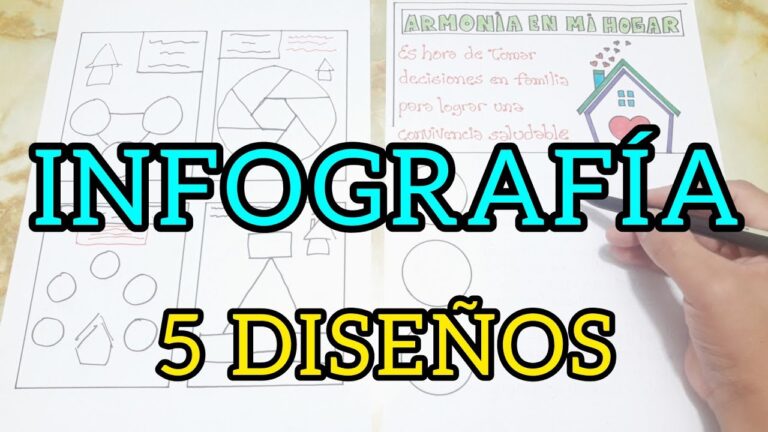
En la era de la información, el diseño de infografías con tipografía adecuada se ha convertido en una herramienta esencial para comunicar datos de manera operativa. La elección de una tipografía apropiada no solo mejora la legibilidad, sino que también refuerza el mensaje visual, capturando la atención del espectador y facilitando la comprensión de conceptos complejos. En este artículo, examinaremos cómo una tipografía bien seleccionada puede transformar una simple infografía en una poderosa narrativa visual que destaque en un mundo saturado de información.
¿Qué tipo de fuente se recomienda para una infografía?
Para una infografía operativa, es recomendable utilizar tipos de letra como Verdana, Arial o Helvética, que son sans serif y garantizan una buena legibilidad. El tamaño de la letra debería estar entre 12 y 14 puntos, lo que permite que la información sea fácilmente visible sin ser abrumadora. Además, es aconsejable reservar el uso de mayúsculas únicamente para palabras cortas y títulos, asegurando así que el contenido se mantenga claro y atractivo para el lector.
¿Qué se debe incluir en la fuente de una infografía?
En una infografía, la fuente es esencial para dar credibilidad a la información presentada, ya que señala de dónde se ha obtenido. Generalmente, se coloca en un tamaño menor y en una ubicación discreta, de manera que no distraiga la atención del lector del contenido principal. Este detalle no solo respeta los derechos de autor, sino que también permite al público profundizar en el tema si lo desea, fomentando una comprensión más rica y fundamentada de los datos expuestos.
¿Cuáles son las mejores fuentes para utilizar en infografías?
Al crear infografías operativas, la elección de la tipografía es fundamental. Las fuentes sans serif, como Roboto, Helvetica y Arial, son especialmente populares debido a su claridad y modernidad. Estas fuentes aportan un aire contemporáneo y facilitan la lectura, lo que las convierte en una excelente opción para captar la atención del espectador.
Para maximizar el impacto visual de tu infografía, es crítico utilizar estas fuentes en los lugares adecuados. Mientras que las fuentes serif suelen ser más apropiadas para el cuerpo del texto, las sans serif brillan en los encabezados de sección, subtítulos, listas y títulos. Este enfoque no solo mejora la estructura visual, sino que también guía al lector a través de la información presentada.
En resumen, la combinación de fuentes adecuadas puede transformar una infografía ordinaria en una herramienta poderosa de comunicación. Al optar por fuentes como Roboto, Helvetica o Arial para los elementos destacados, aseguras que tu mensaje sea claro y atractivo, manteniendo al espectador interesado y comprometido con el contenido.
Tipografía que Captura: Clave de una Infografía Exitosa
La tipografía es un elemento fundamental en el diseño de infografías, ya que no solo comunica información, sino que también establece el tono y la personalidad del mensaje. Elegir fuentes adecuadas puede transformar una presentación visual, haciendo que los datos sean más accesibles y atractivos. La combinación de diferentes estilos tipográficos, siempre manteniendo la coherencia, puede guiar al espectador a través de la narrativa visual, destacando los puntos clave sin perder claridad.
La legibilidad debe ser una prioridad al seleccionar tipografías. Fuentes simples y limpias, como sans-serif, suelen ser las más operativas para transmitir información de manera rápida y eficiente. Además, el tamaño de la fuente y el contraste con el fondo son aspectos fundamentales que determinan la facilidad con la que se puede leer el contenido. Un diseño bien equilibrado entre texto e imágenes no solo retiene la atención del espectador, sino que también facilita la comprensión del mensaje.
Finalmente, la jerarquía tipográfica juega un papel esencial en la organización de la información. Usar diferentes tamaños, pesos y estilos ayuda a resaltar lo más importante y a guiar al lector a través de la infografía. Una estructura clara y visualmente atractiva no solo mejora la experiencia del usuario, sino que también potencia la efectividad del mensaje que se desea transmitir. En definitiva, la tipografía es la clave que puede elevar una infografía de ser simplemente informativa a ser verdaderamente impactante.
El Poder de la Letra: Mejora la Comunicación Visual
La comunicación visual es un elemento esencial en el mundo actual, donde la información se consume a un ritmo acelerado. La letra, como componente fundamental del diseño gráfico, juega un papel crítico en cómo se perciben y entienden los mensajes. Al elegir tipografías adecuadas y combinarlas con colores y formas, se puede captar la atención del público de manera operativa, facilitando la comprensión y el recuerdo de la información.
Además, una letra bien diseñada no solo embellece, sino que también transmite emociones y establece la identidad de una marca. La armonía entre la tipografía y los elementos visuales puede transformar un simple mensaje en una experiencia memorable. En un entorno donde la primera impresión cuenta, invertir en una comunicación visual sólida y atractiva es clave para destacar y conectar con la audiencia.
Diseño Atractivo: La Tipografía como Herramienta
La tipografía es un elemento fundamental en el diseño gráfico, ya que no solo transmite información, sino que también establece la personalidad y la emoción de un proyecto. Elegir la fuente adecuada puede ser la clave para captar la atención del público, generando un impacto visual que resuena con la audiencia. Desde tipografías elegantes y clásicas hasta opciones modernas y audaces, cada estilo aporta una atmósfera única que puede hacer que un diseño sea memorable y efectivo.
Además, la tipografía no se limita a ser un mero adorno; es una herramienta poderosa que guía la lectura y la comprensión del contenido. Un buen uso de la jerarquía tipográfica permite resaltar los elementos más importantes, facilitando así la navegación y mejorando la experiencia del usuario. Al combinar estética y funcionalidad, los diseñadores pueden crear composiciones armoniosas que no solo atraen miradas, sino que también comunican mensajes claros y directos.
Mensajes Claros: La Tipografía que Impacta
La tipografía es un elemento crítico en la comunicación visual, ya que tiene el poder de transmitir emociones y mensajes de manera operativa. Elegir la fuente adecuada no solo mejora la legibilidad, sino que también establece el tono de la información presentada. Una tipografía bien seleccionada puede captar la atención del lector en cuestión de segundos, haciendo que el contenido resuene y se recuerde con mayor facilidad.
En un mundo saturado de información, los mensajes claros son esenciales para destacar. Las fuentes limpias y modernas, como Helvetica o Arial, ofrecen una apariencia profesional y accesible, mientras que las tipografías más creativas pueden añadir un toque de originalidad. Al combinar estilo y funcionalidad, se logra un impacto visual que no solo atrae, sino que también comunica de manera operativa, convirtiendo ideas complejas en conceptos fácilmente digeribles.
El diseño de infografías con tipografía adecuada no solo mejora la estética visual, sino que también potencia la comprensión y retención de la información. Al elegir fuentes que se alineen con el mensaje y la audiencia, se crea una conexión más operativa y atractiva. En un mundo donde la comunicación visual es esencial, invertir en una tipografía bien seleccionada puede marcar la diferencia entre un mensaje olvidado y uno que perdura en la memoria.